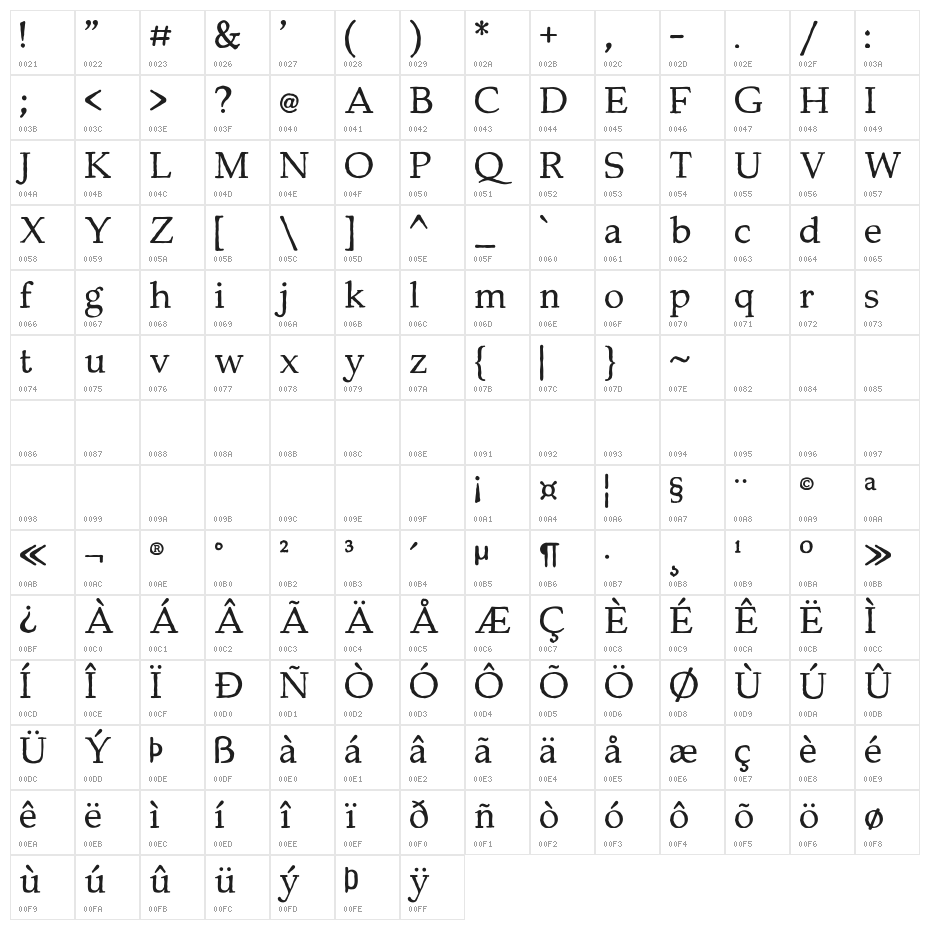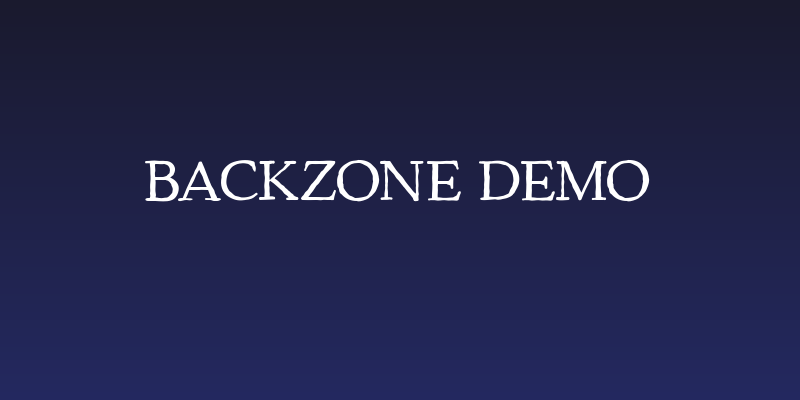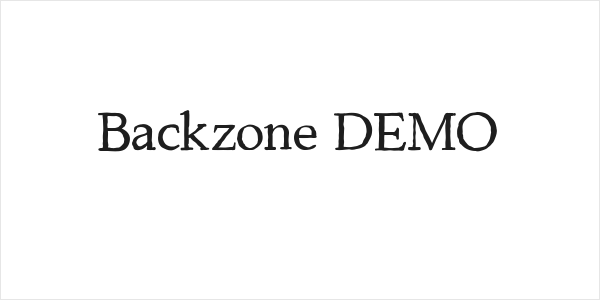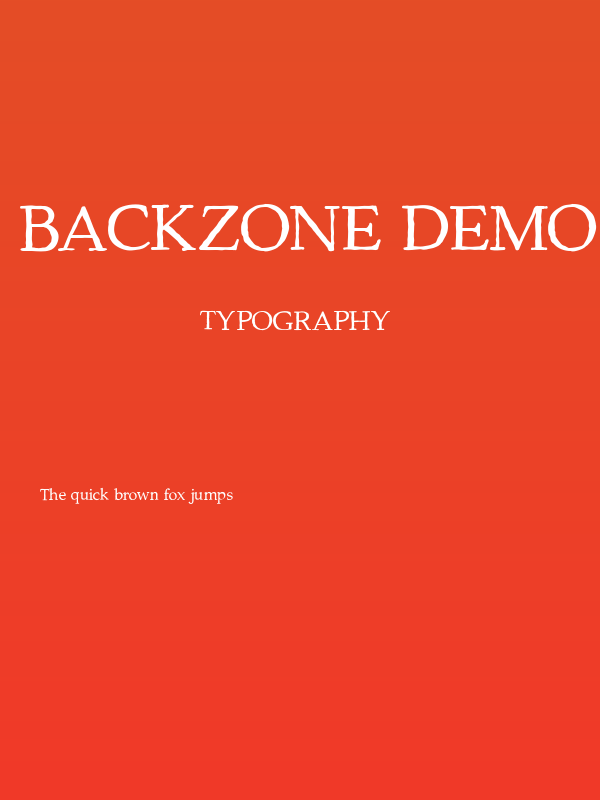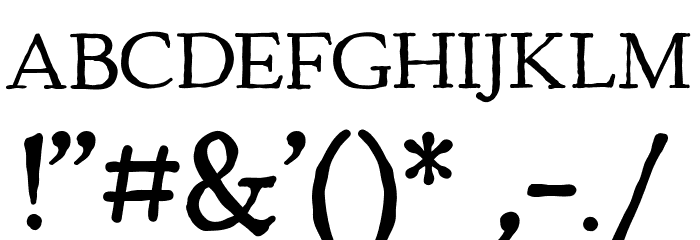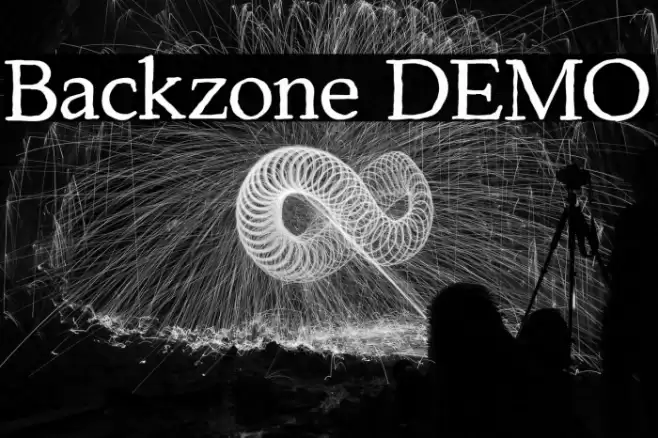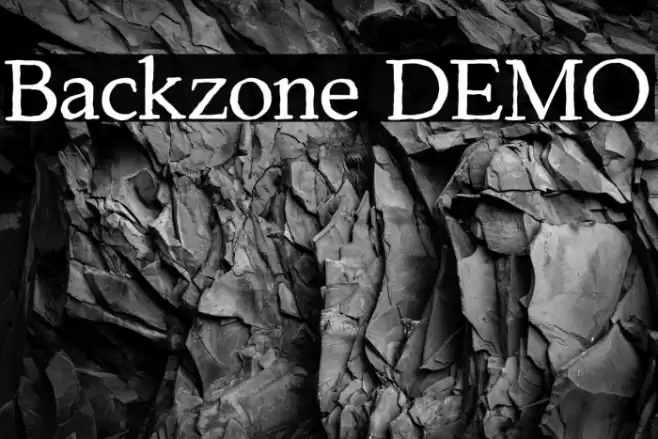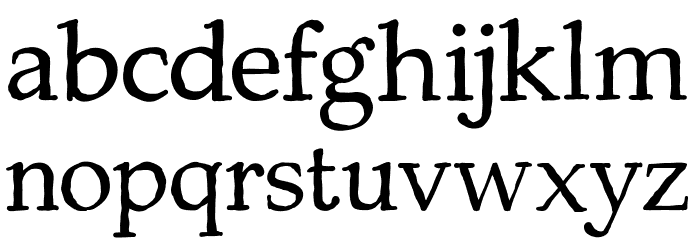
Backzone DEMO Font
✎ Serif
| Kategorien | Serif |
| Gesamtstil | Vintage |
| Anwendungsfall | Headlines, Body text, Logos |
| Vorgeschlagene Projekte | Ideal for projects that require a vintage or classic touch, such as book covers, invitations, branding for artisanal products, or historical-themed designs. |